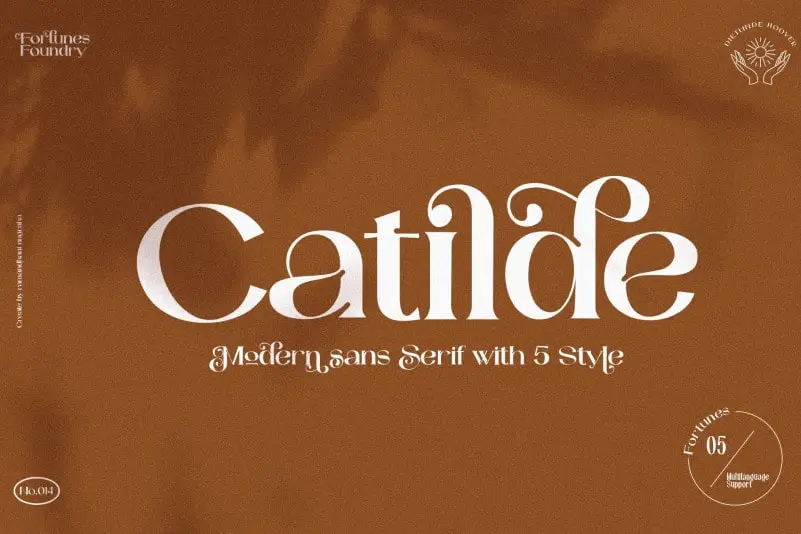
Catilde Serif Font – Fonte Grátis
Catilde Serif Font
A Catilde Serif Font é uma escolha perfeita para aqueles que buscam elegância sofisticada em cada projeto visual. Com seu aspecto delicado e arredondado, essa serif se destaca por suas linhas finas e robustas, criando um tom de luxo e sofisticação. Essa fonte vem com cinco diferentes estilos, perfeita para uma variedade de aplicações, como marca, revistas, logos, convites, headlines, anúncios, e muito mais. A Catilde Serif é a escolha ideal para quem busca tanto beleza quanto funcionalidade em sua próxima obra gráfica.